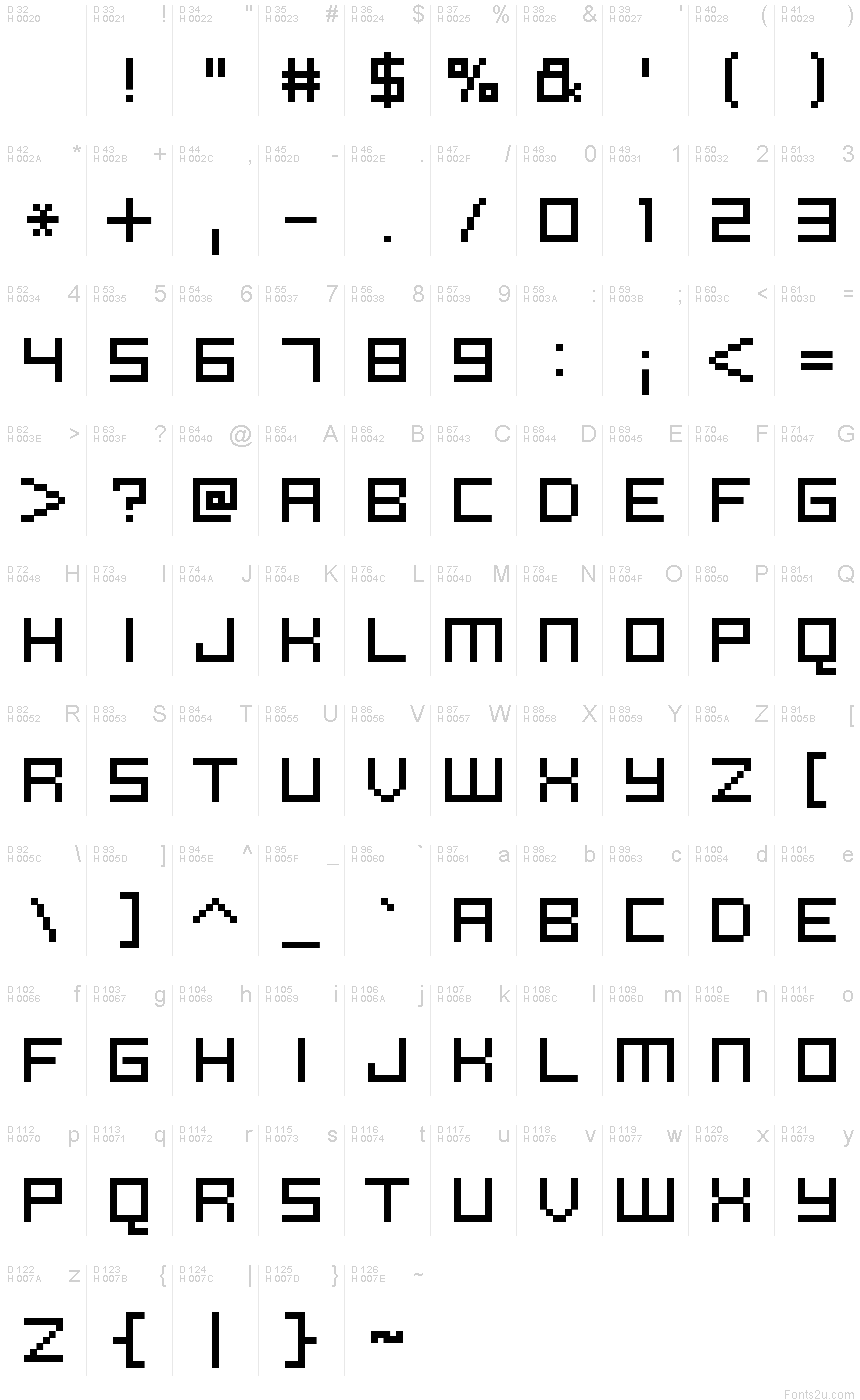
Podgląd czcionki NK22
NK22 autorstwa Nikoli Kovanovica to darmowy cyrylicki font bitmapowy o wyrazistym, modularnym rytmie. Litery zbudowane są z kwadratowych kątów i równych kresek, co nadaje krojowi surowy klimat wczesnych ekranów, plasujący go gdzieś pomiędzy szyldami a grafiką ze starych gier.
Krój sprawdza się w tytułach plakatów, ulotkach klubowych, okładkach zinów, planszach tytułowych i krótkich nagłówkach redakcyjnych, gdzie siatkowa tekstura może zdominować stronę. Jako darmowy font, NK22 świetnie nadaje się również do monogramów i inicjałów, ponieważ jego blokowe sylwetki najlepiej prezentują się wtedy, gdy pozwolisz, by kilka dużych liter mówiło samo za siebie.